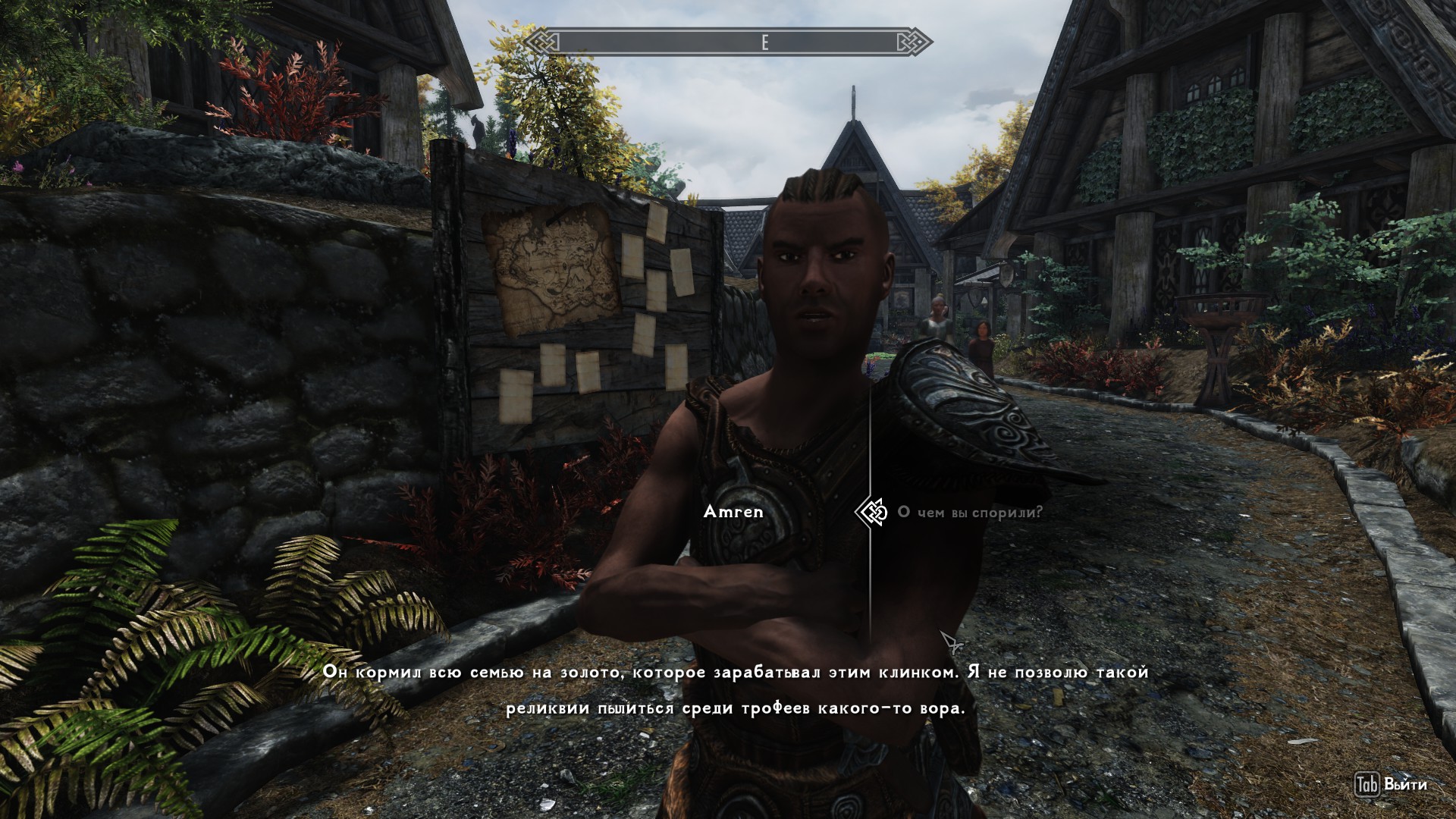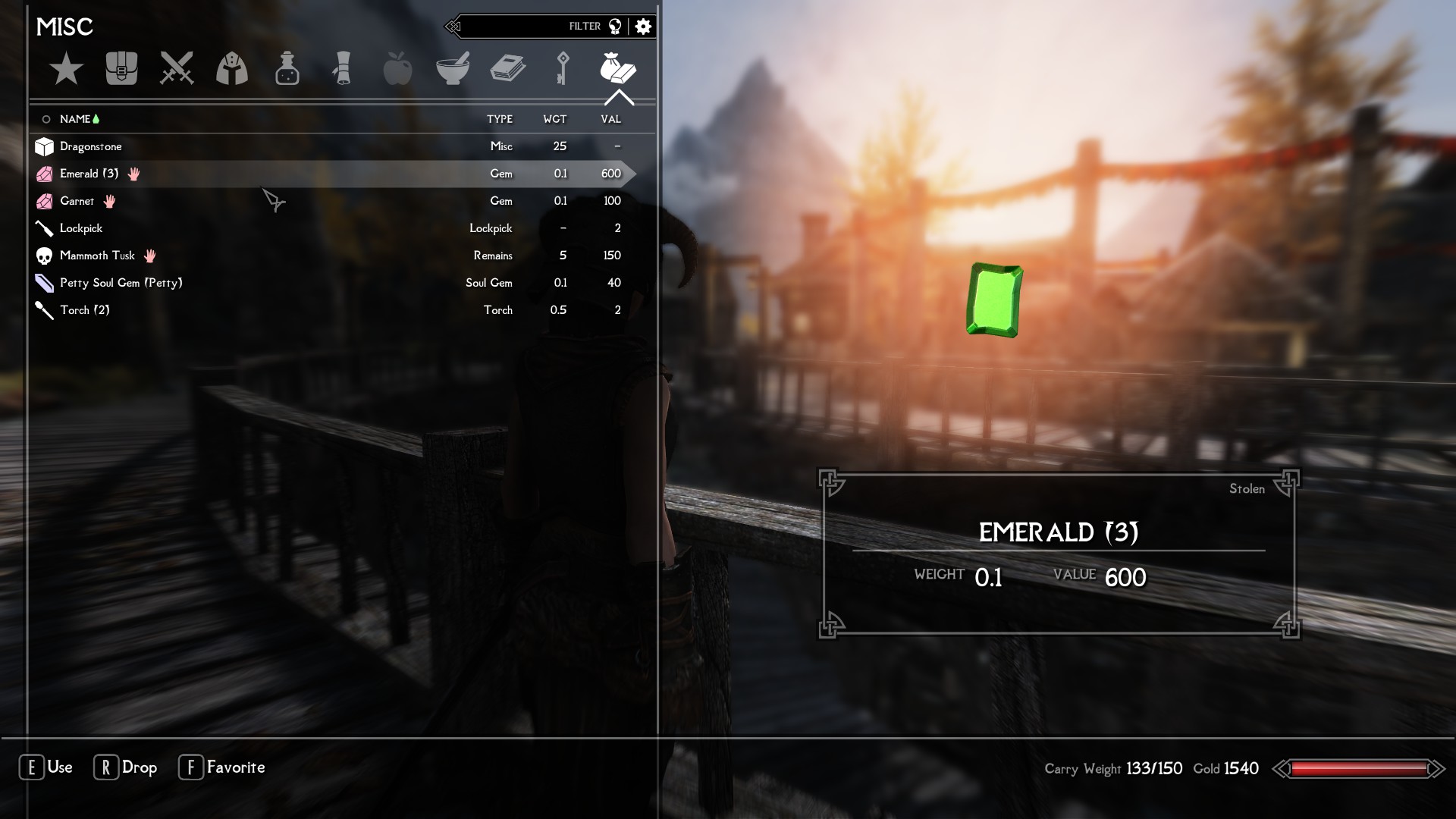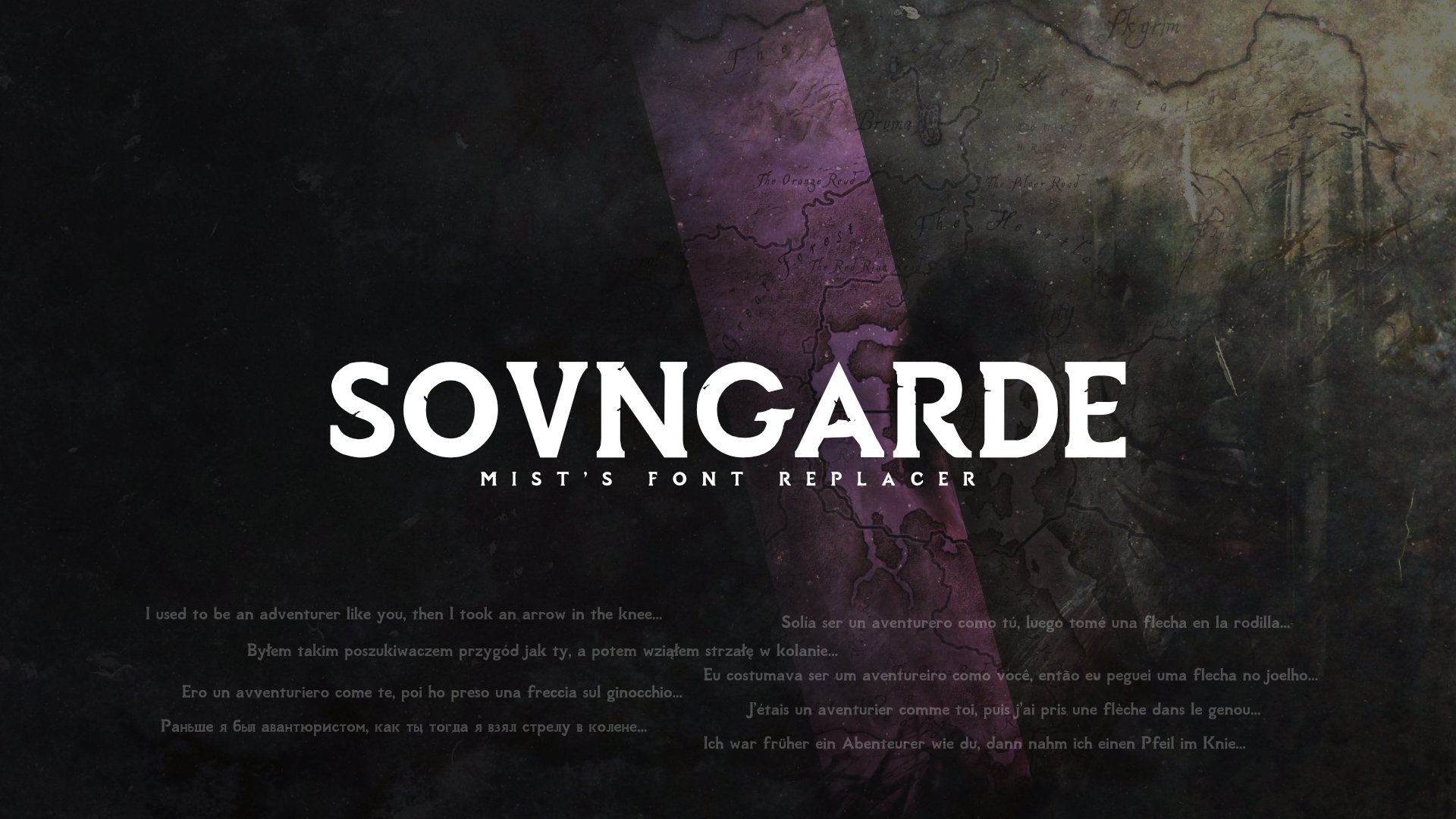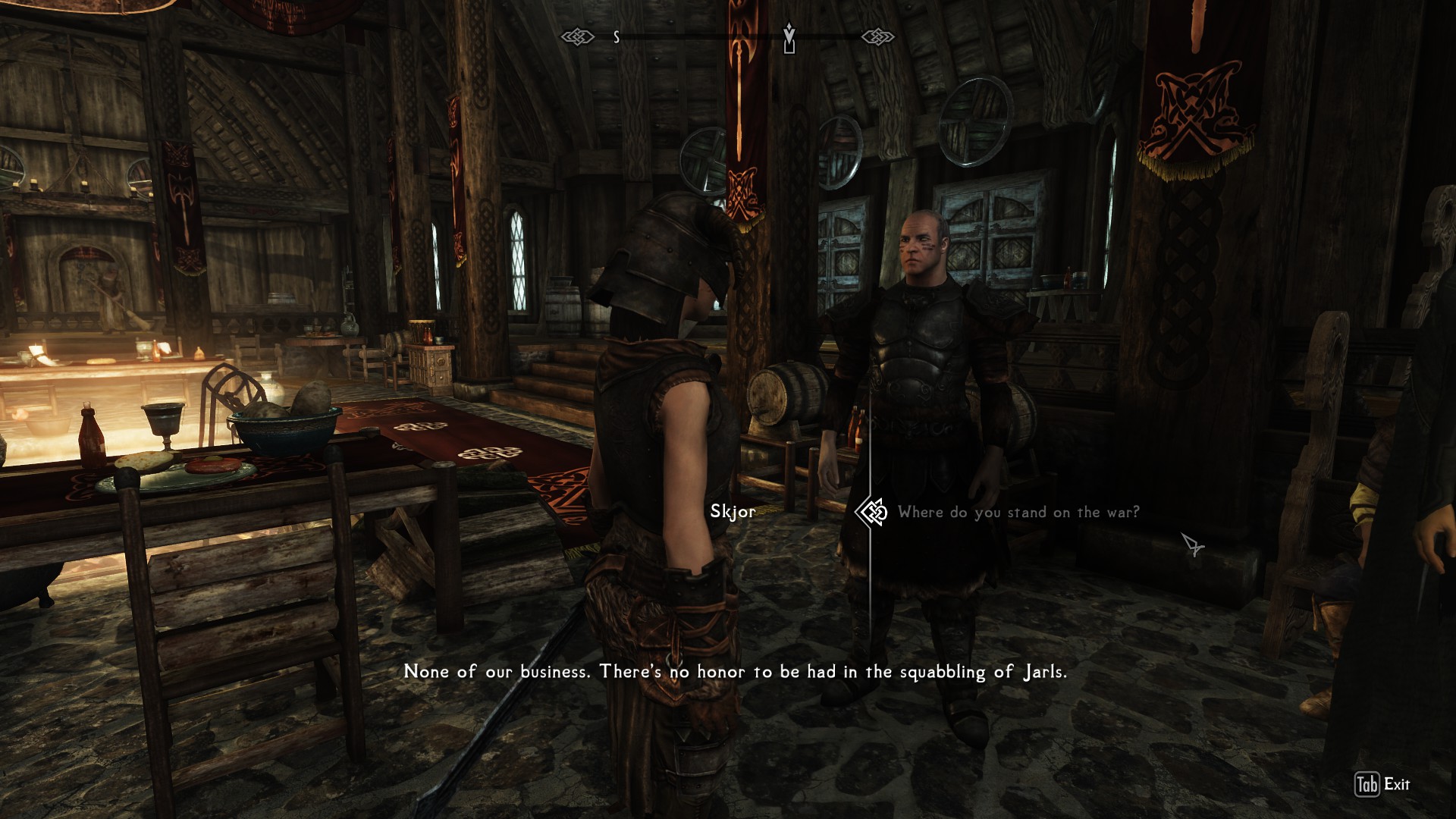
Sovngarde - Тематический игровой шрифт 8.9
Sovngarde - тематический игровой шрифт. Разработан для усиления погружения в сеттинг игры Skyrim. Создан с поддержкой 8 языков, но в данном архиве предпочтение отдаётся русскому.
Имеет 2 стиля:
+ Light - менее жирный вариант написания, близок к стоковому шрифту по весу. Находится в папке "Light".
+ Bold - более жирный вариант написания, если вам кажется, что буквы "теряются" на экране. Находится в папке "Bold".